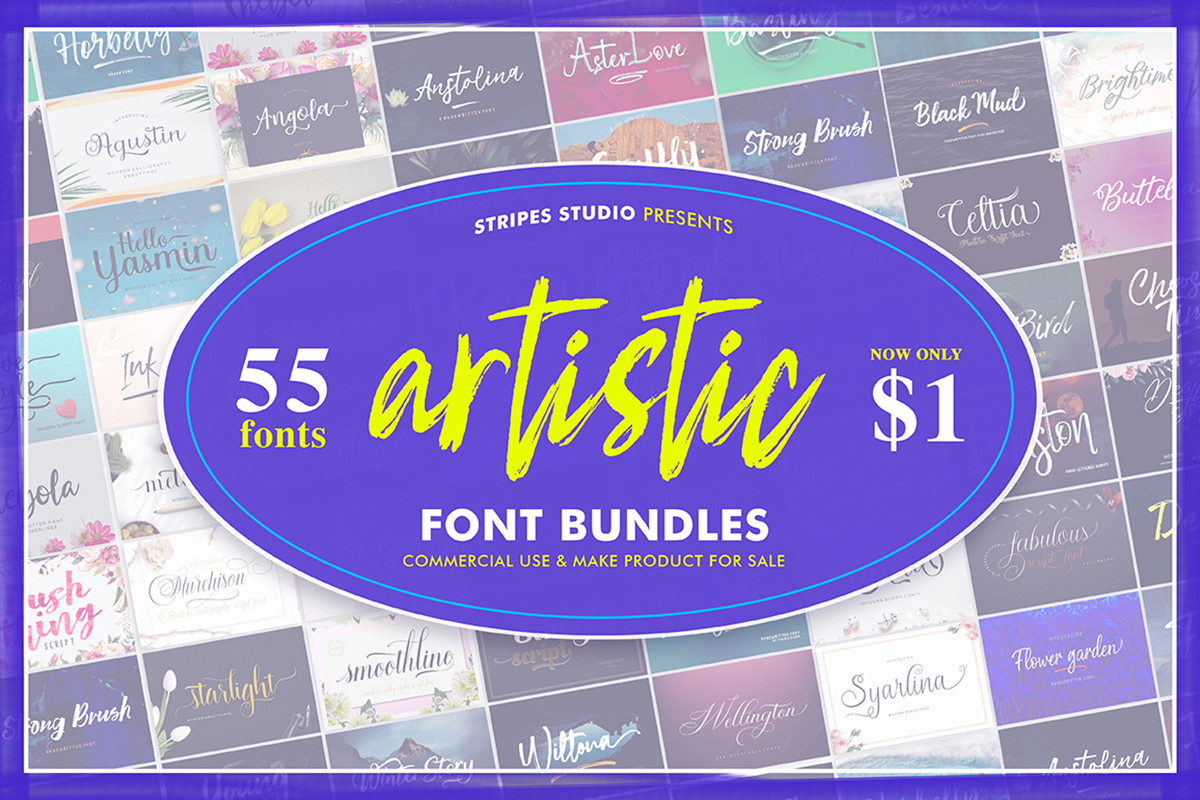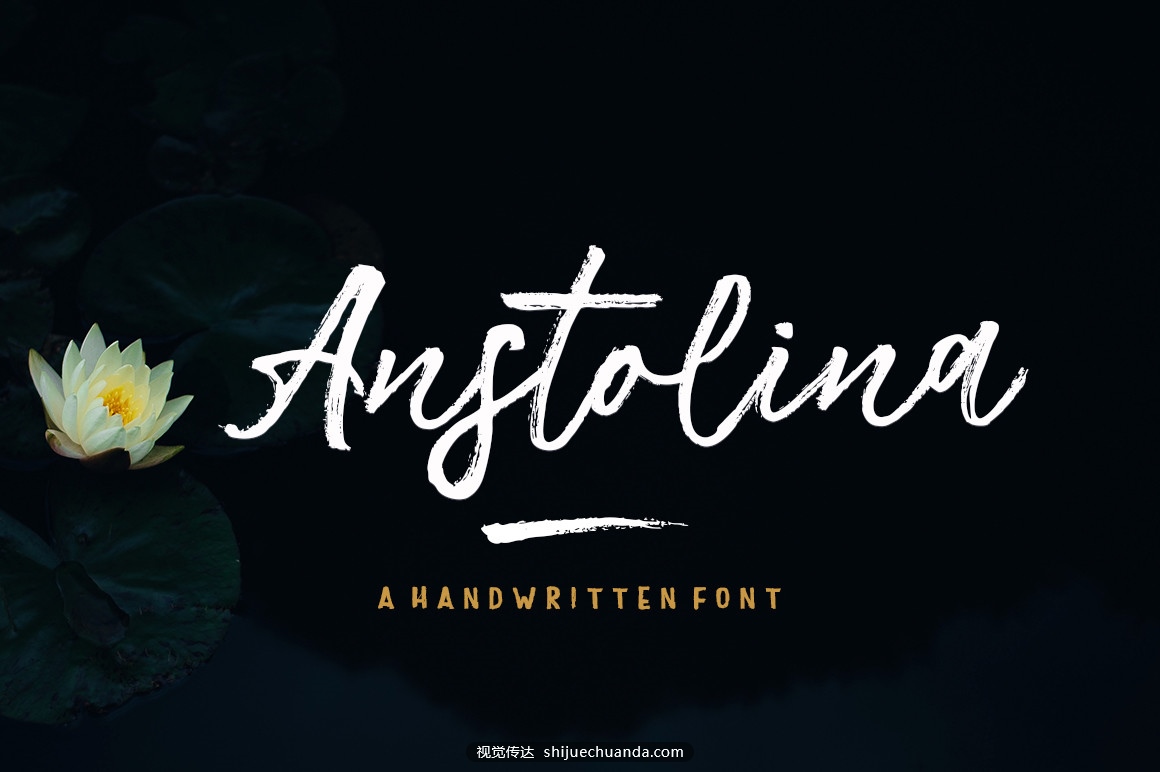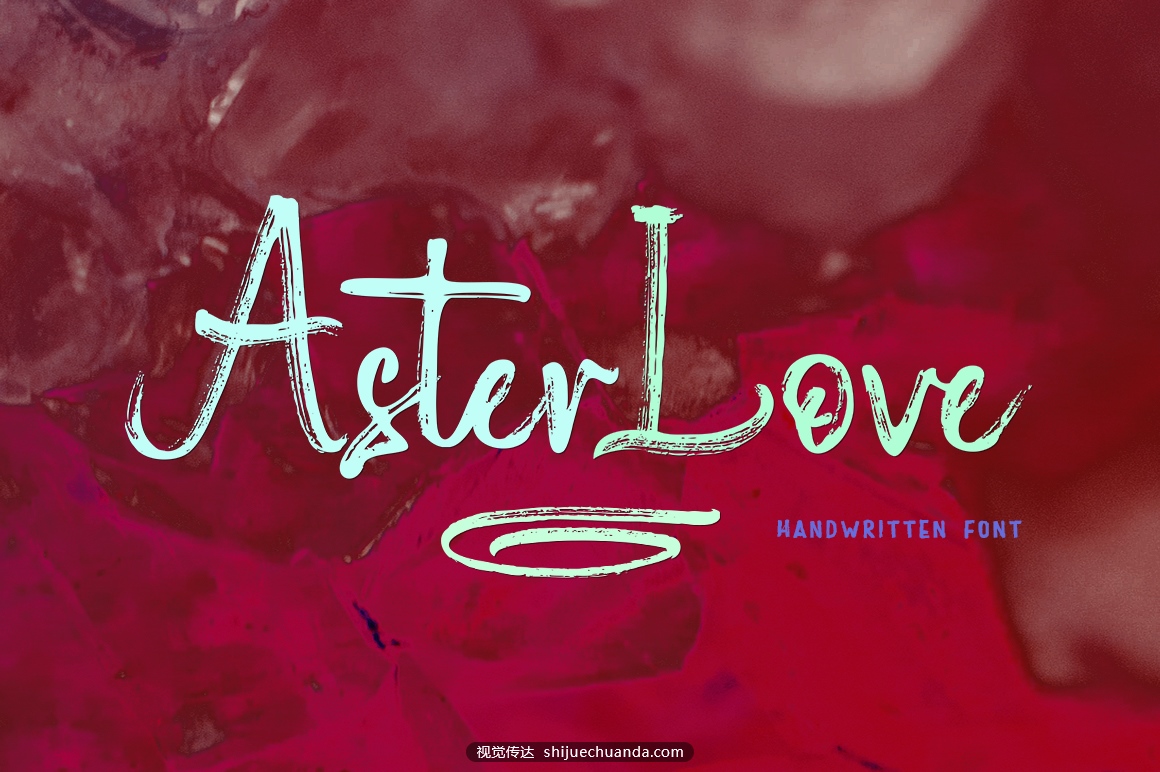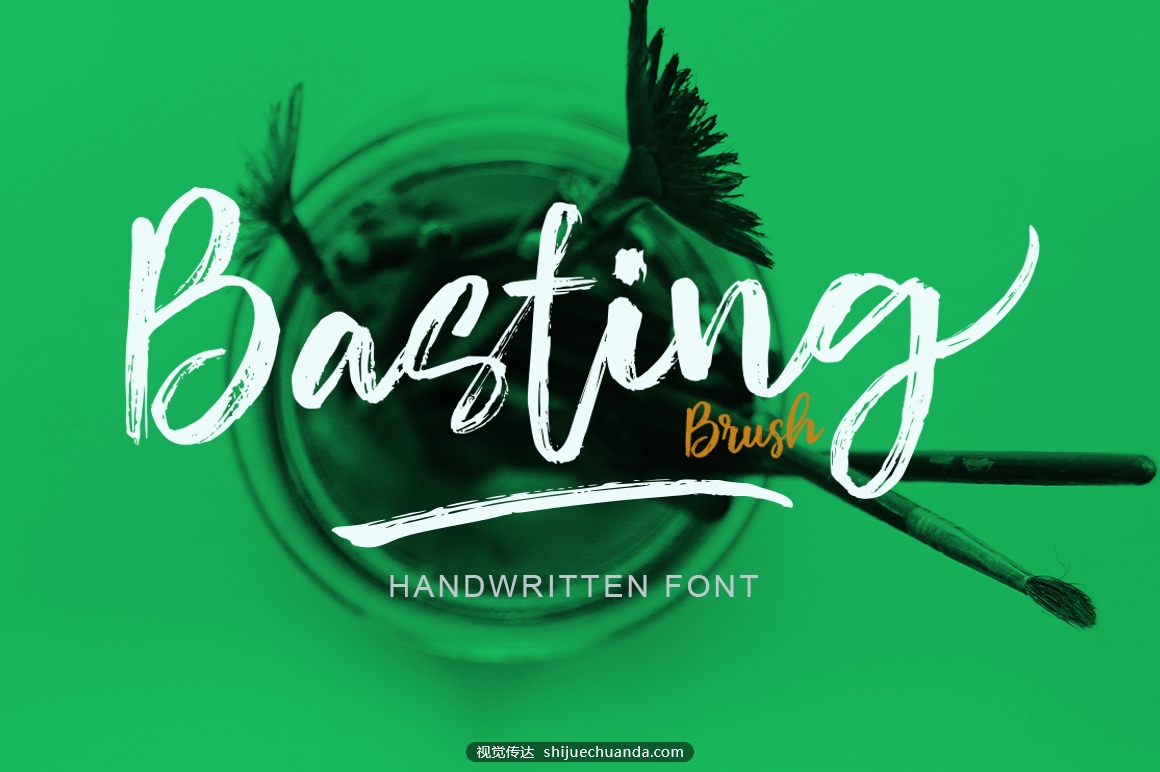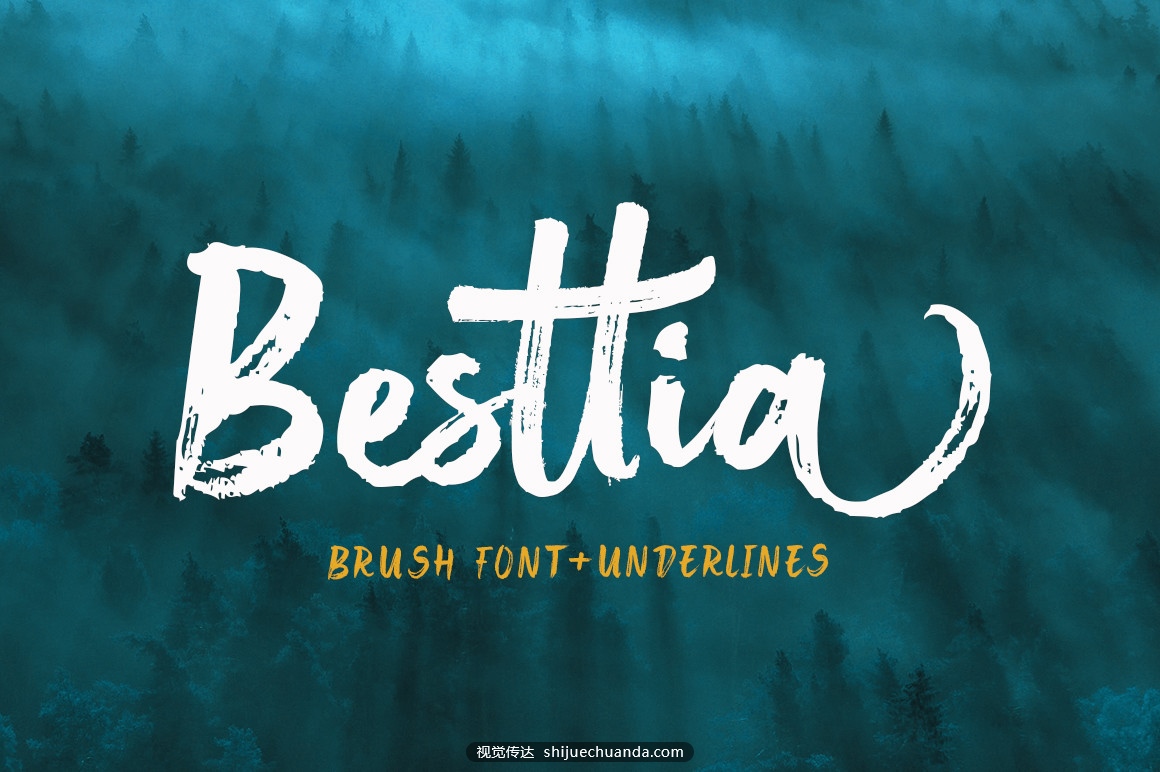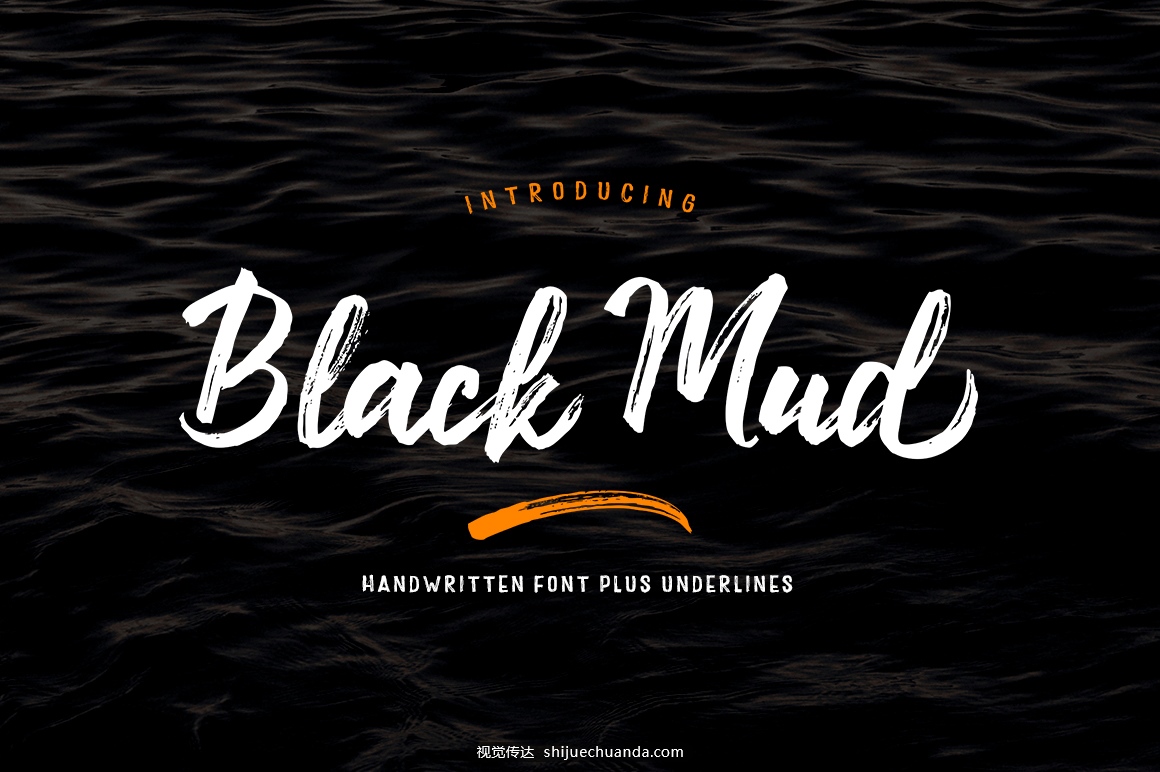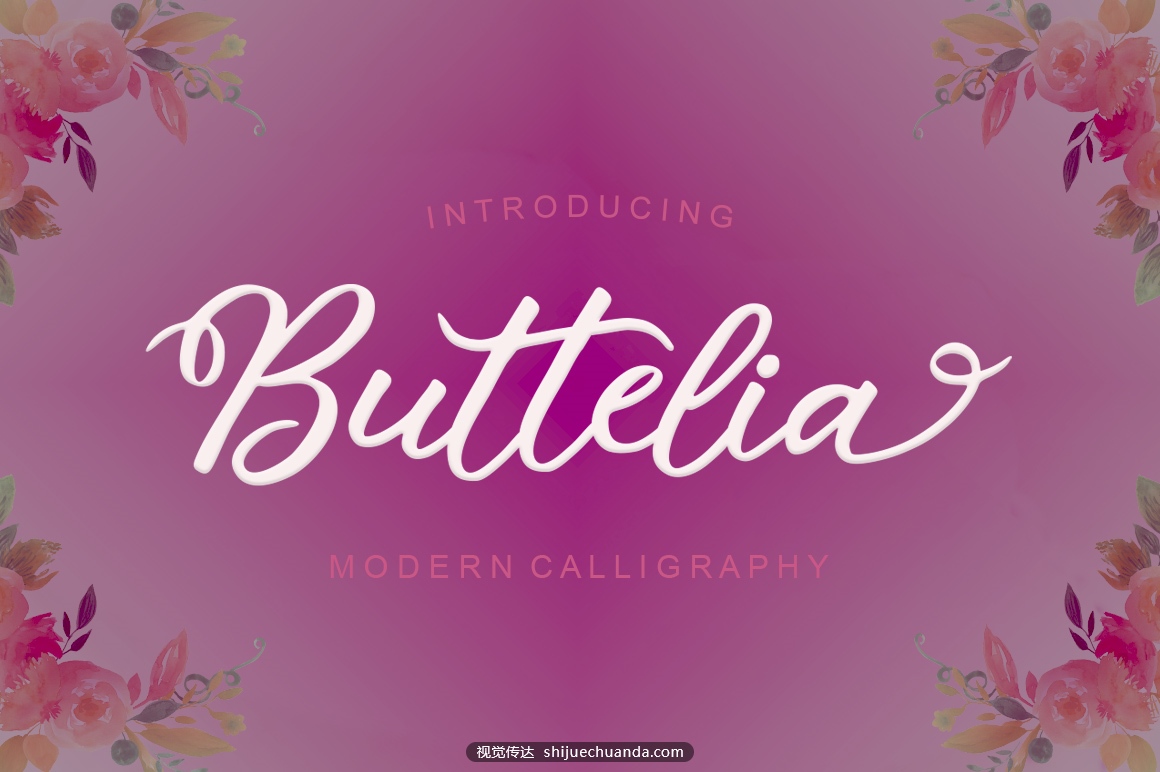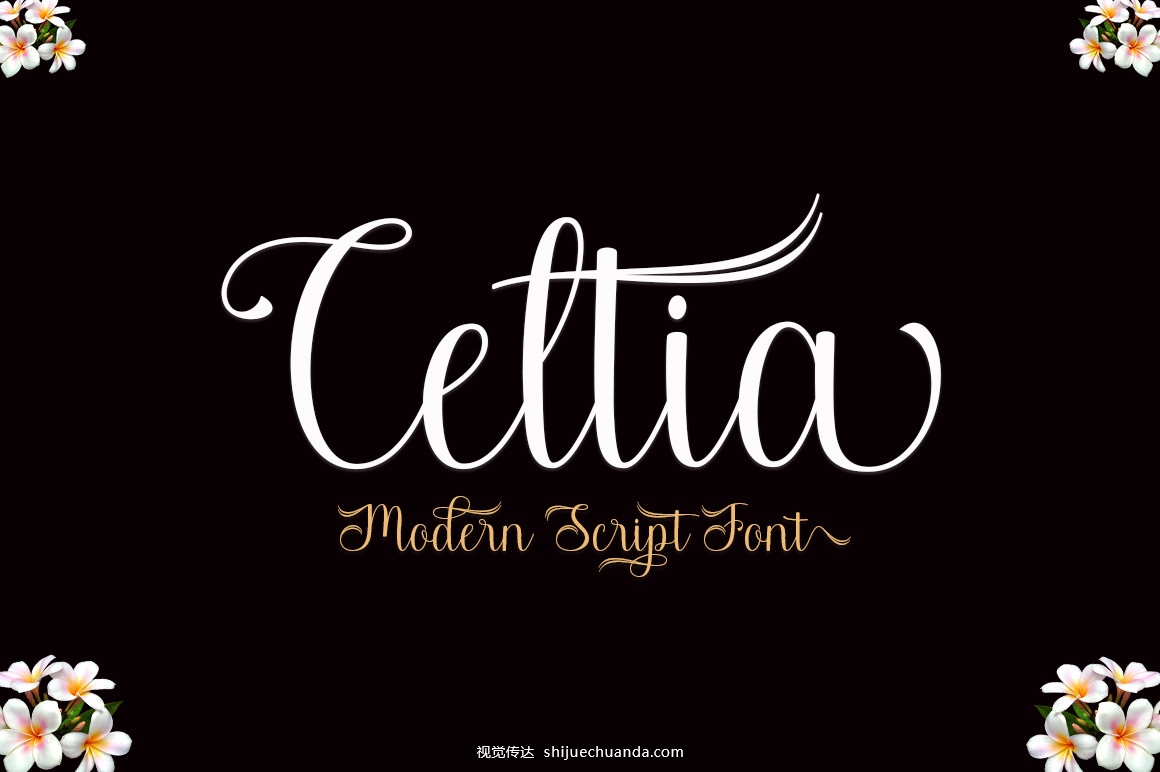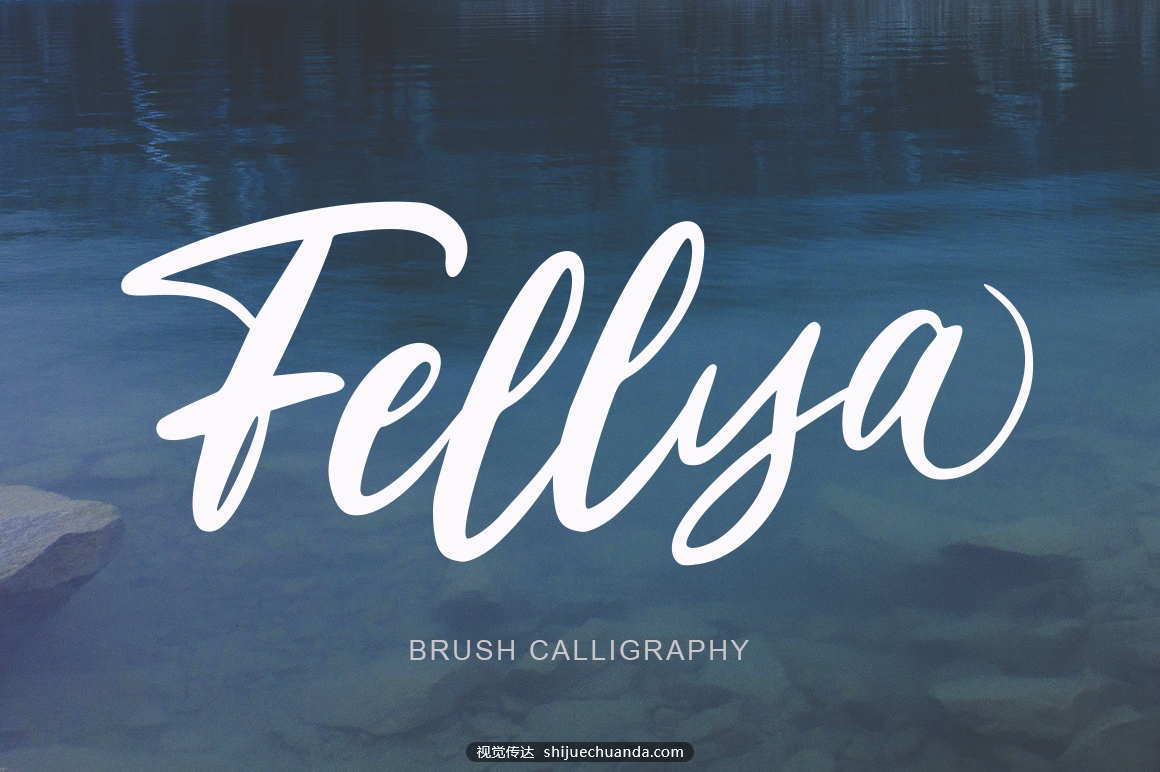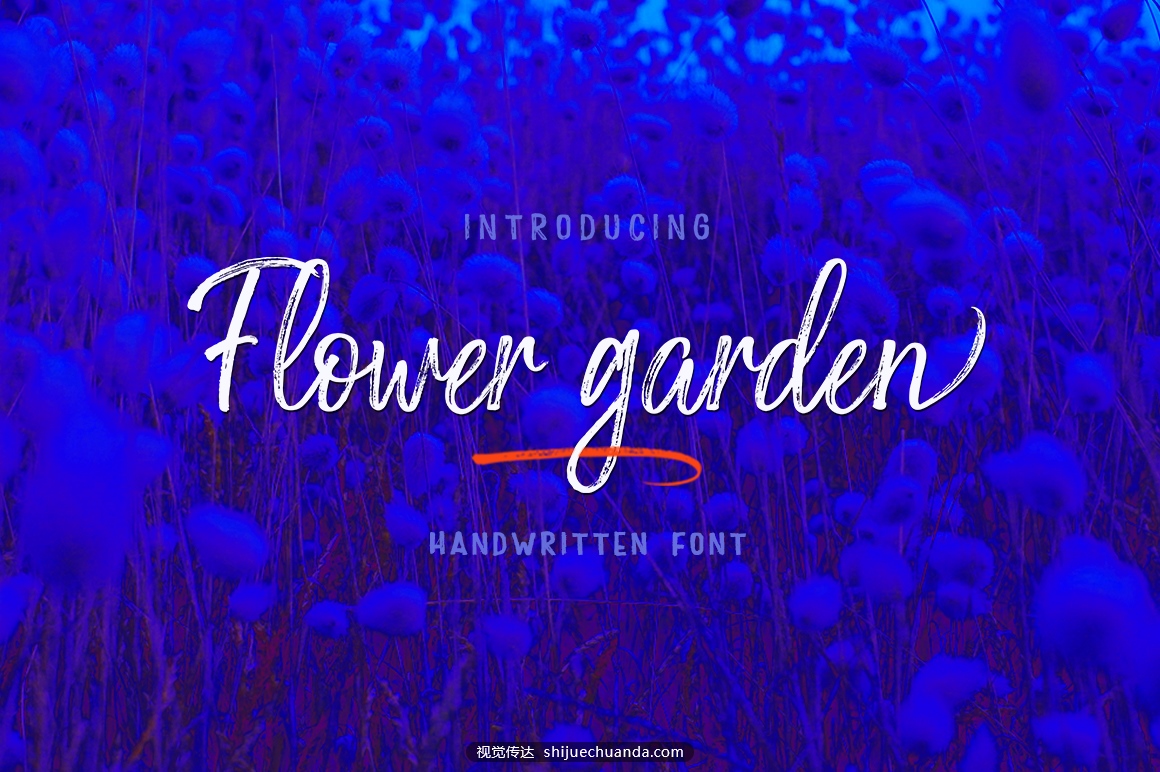
手写艺术字体包 Artistic Font Bundles
Artistic Font Bundles 包含 55 种华丽的字体。该集合包括各种字体样式。还支持 PUA 编码。Access字体字符与Silhouette Studio、Cricut Design Space等兼容。您可以轻松访问所有字形和花体!